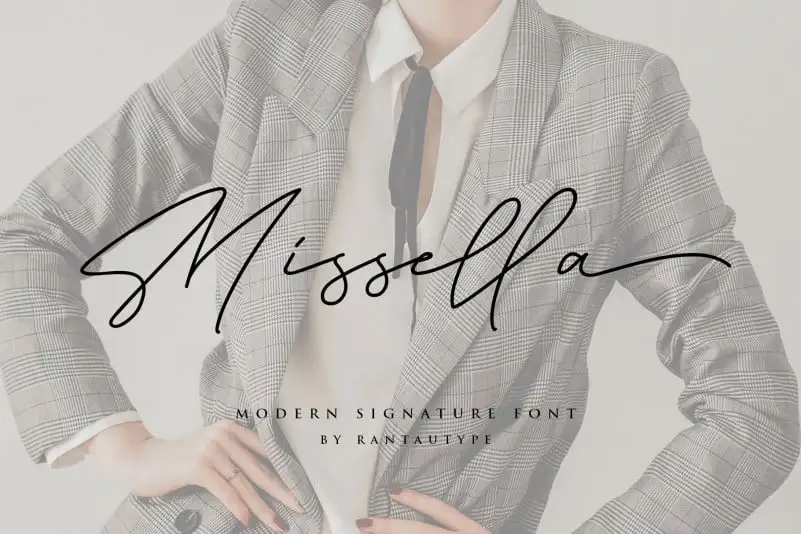
A Missella Handwritten Font é uma elegante tipografia feita à mão que se destaca entre as demais. Ela é fruto do talento artesanal dos criadores da Rantau Type, oferecendo um estilo distinto e relaxado, com sua caligrafia suave e delicada, que transmite leveza feminina. Esta fonte é perfeita para os projetos mais sofisticados onde uma pegada elegante é desejada. Ela é ideal para aplicações como logotipos de assinatura, cartões de visita, capas de álbuns e até mesmo watermark em fotos ou citações. Missella traz um toque especial aos seus trabalhos, elevando-os a um nível superior. Para designers que buscam uma fonte suave e elegante para seus projetos gráficos, Missella é uma escolha ótima. Seja por sua aplicação em cartões de visita ou capas de álbuns, ou mesmo em obras de arte que desejam transmitir um certo toque profissional, esta fonte tem tudo o que você precisa para dar seu projeto aquela pegada perfeita e única. Com a Missella Handwritten Font, suas criações se destacarão em qualquer plataforma onde ela seja utilizada.